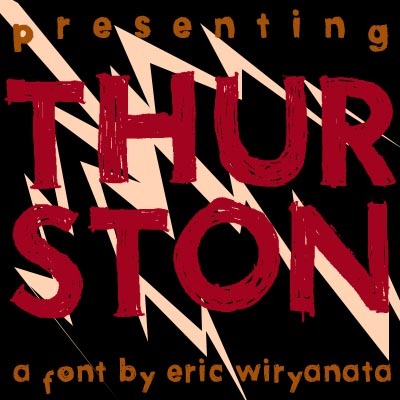
Thurston, eine kostenlose, raue Display-Schrift von Typeface High-Logic, vermittelt das Flair handgemalter Schilder und traditioneller Holzschnitte. Die Großbuchstaben wirken wie eingekratzt und abgenutzt – mit ungleichmäßigen Kanten, kräftigen Strichen und einer unruhigen, tintenverlaufenden Textur, die den Buchstaben ihre rohe, ungekünstelte Ausstrahlung verleiht.
Perfekt für Plakat-Überschriften, Band-Flyer, Horror-Layouts, Titelkarten sowie Pub- oder Festival-Branding, bei denen ein kostenloser Font Charakter zeigen soll, ohne ins Spielerische abzudriften. Die breite Formensprache sorgt für eine direkte, prägnante Botschaft, während die abgenutzte Oberfläche kurzen Wörtern, Monogrammen und Initialen einen authentischen, handgefertigten Kick verleiht.
Der Name „Thurston“ wurde in Anlehnung an Thurston Moore gewählt.
Das Design steht in keinem Zusammenhang mit Thurston Moore; der Name wurde lediglich ausgewählt, weil er gut zur Schrift passte.
Die Schrift basiert auf Skizzen, für die Futura als Inspiration diente.
Einige Illustrationen sind direkt in die Schrift eingebettet.